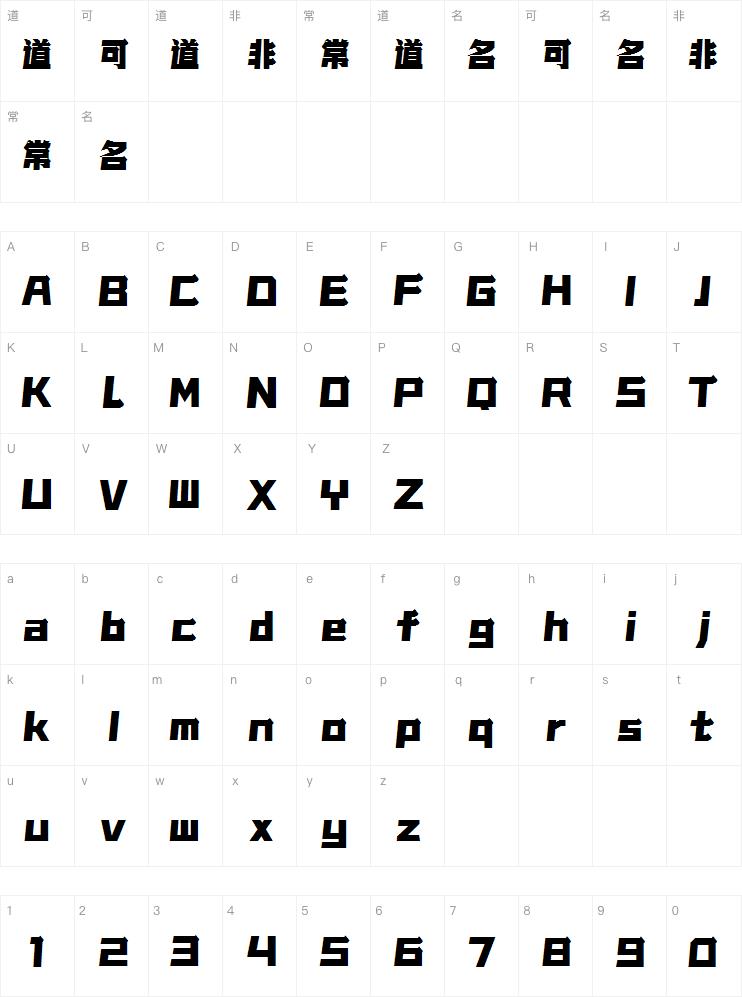
锐字潮牌挑战简 超宋是一款年轻动感,彰显自信用于挑战的体育精神的创意宋黑。字型整体单边结构倾斜设计,结合斜切的起笔与笔锋向上扬起的收笔设计,带给整体昂扬向上的精神面貌,既有年轻向上的进取,又不失自信稳重的坚定。宋体笔画以更加直接的方式平衡版面中的人文风格与现代简洁风格,新颖的字型设计彰显运动健将不断突破自我的顽强精神,适用于体育精神宣传、招牌、节日宣传等场景。